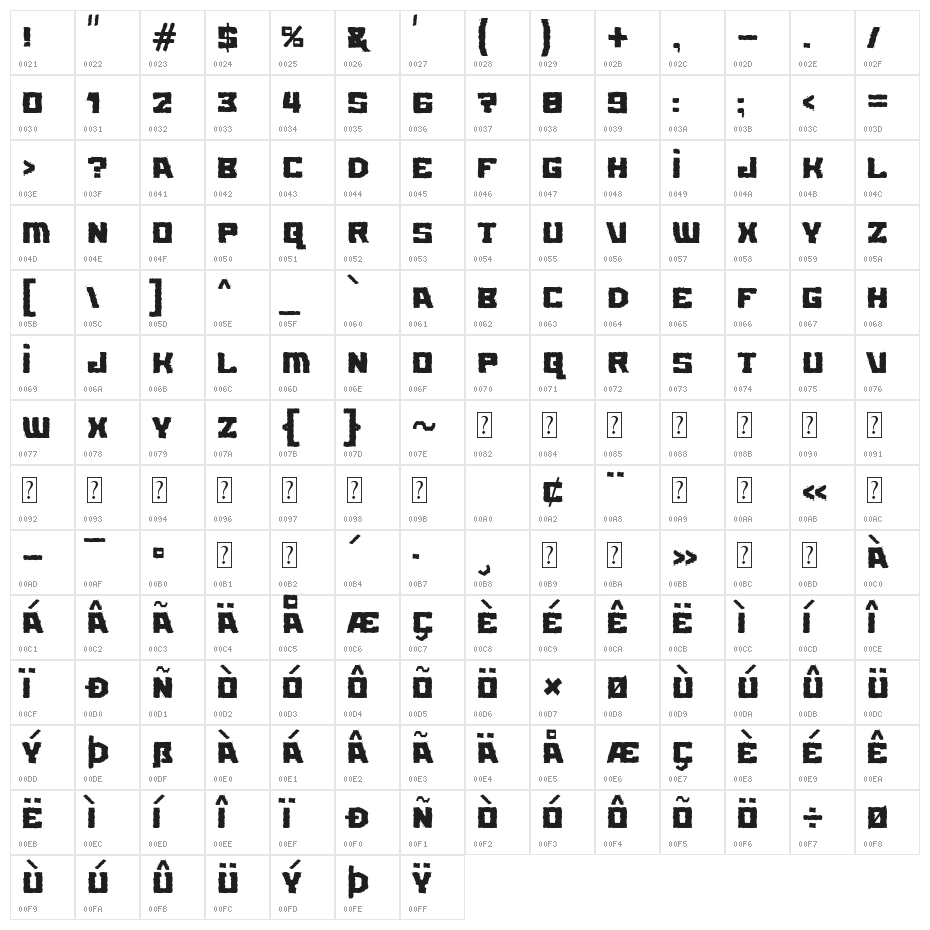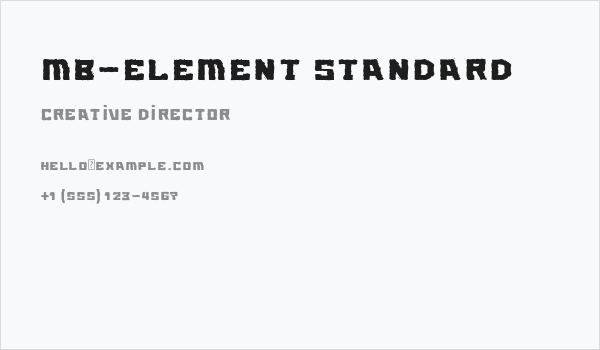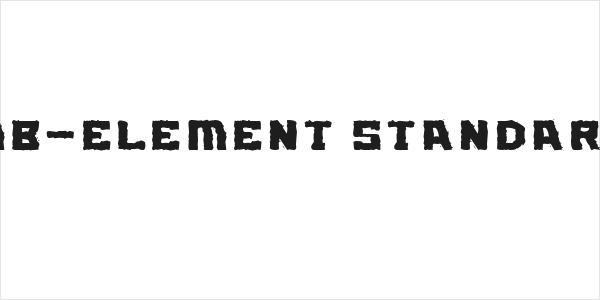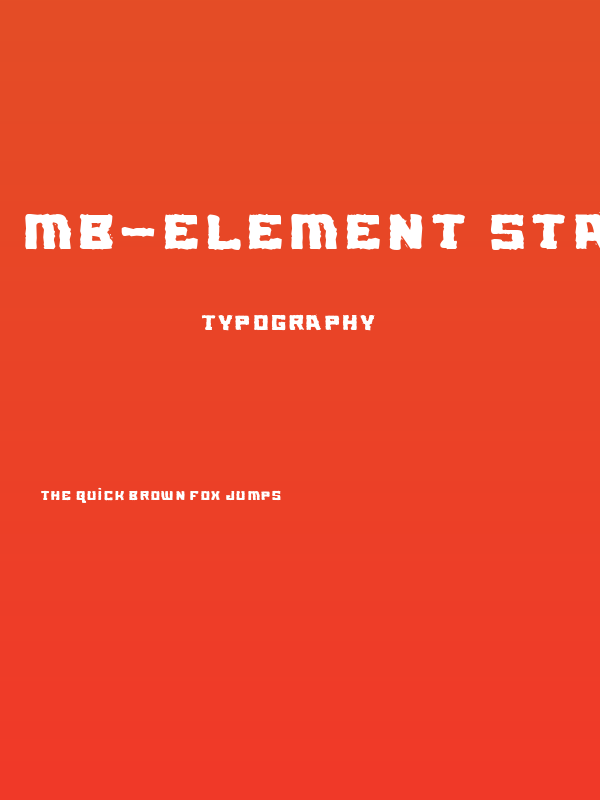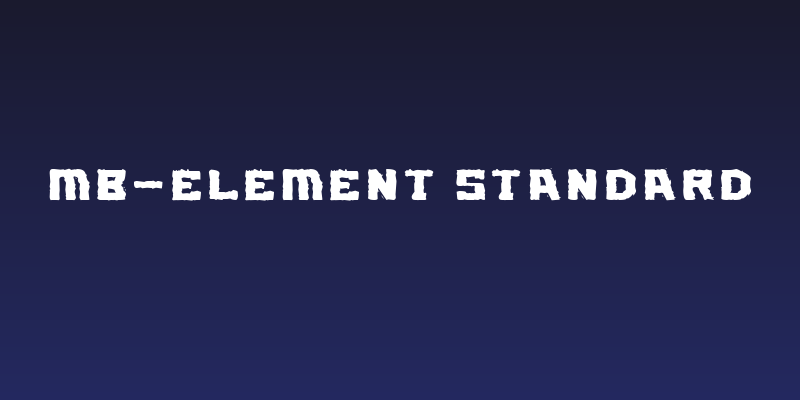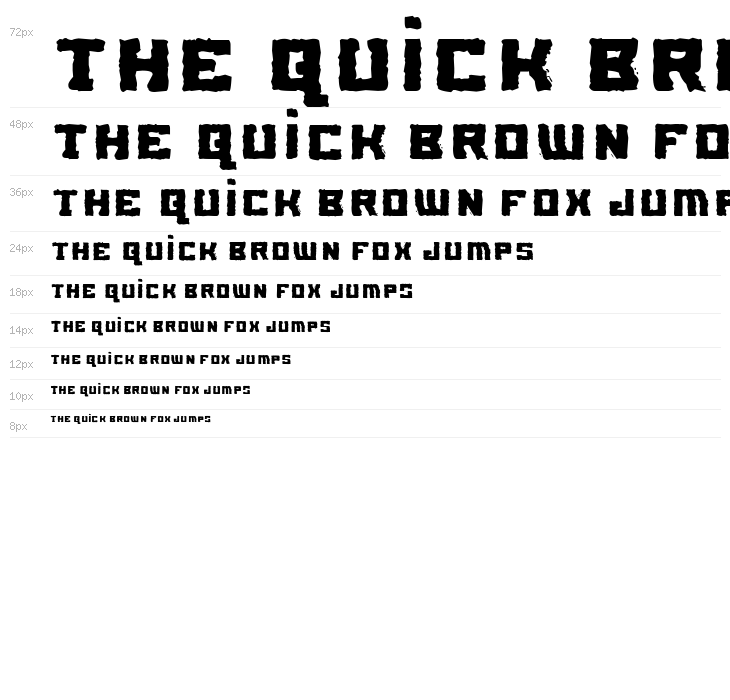
MB-Element Standard Font
✎ Distorted Eroded
| Progetti proposti | Ideal for posters, album covers, branding for outdoor or adventure-themed products, and any design requiring a bold, impactful look. |